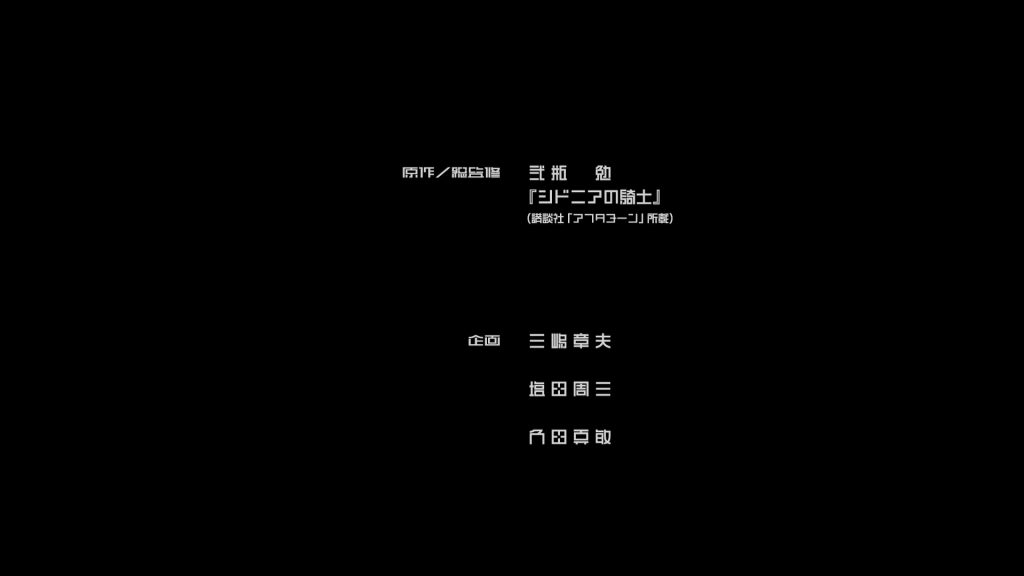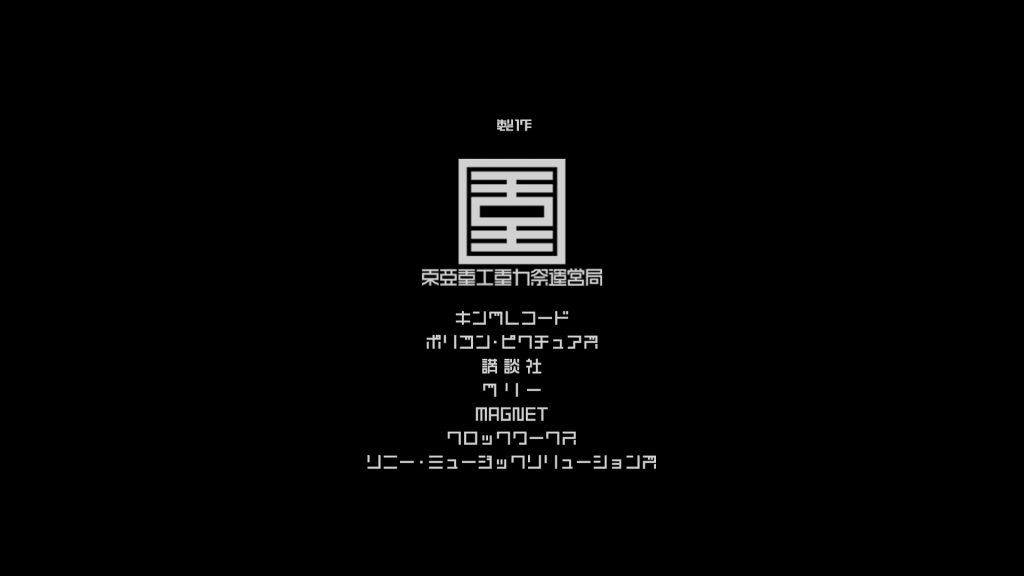
東亜重工映像
東亜重工重力祭運営局
採用事例(製品名)映画「シドニアの騎士 あいつむぐほし」
使用書体東亜重工製フォント『東亜重工』
事例紹介文東亜重工製フォント『東亜重工』は、漫画家の弐瓶氏原案、監修のもと同氏の世界観をイワタが新たに形にしたフォントです。
2021年6月に公開された、映画『シドニアの騎士 あいつむぐほし』のエンドロールや販促物に採用されました。